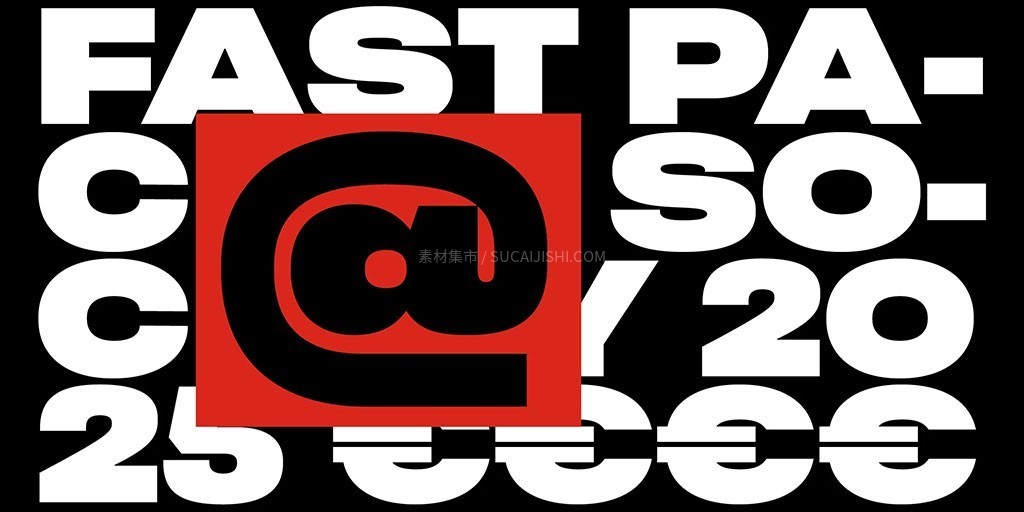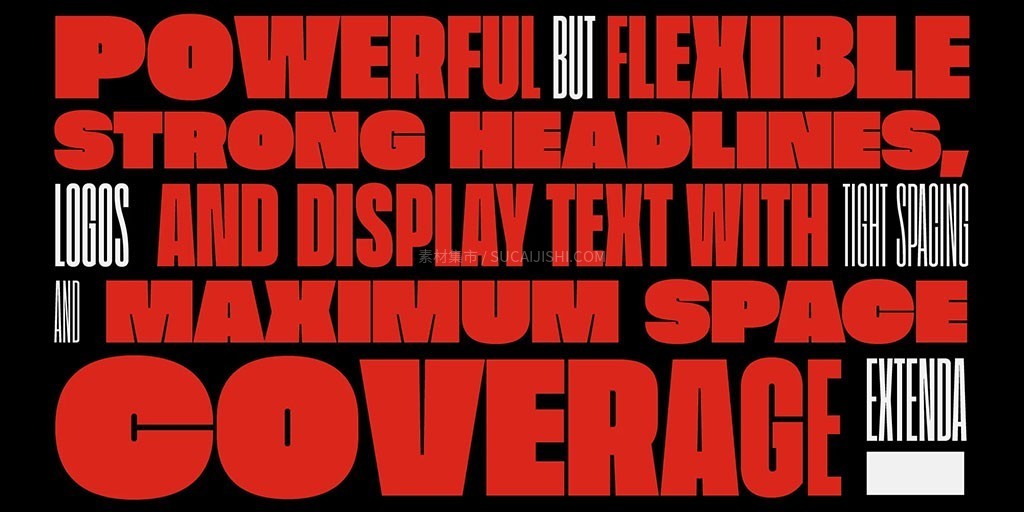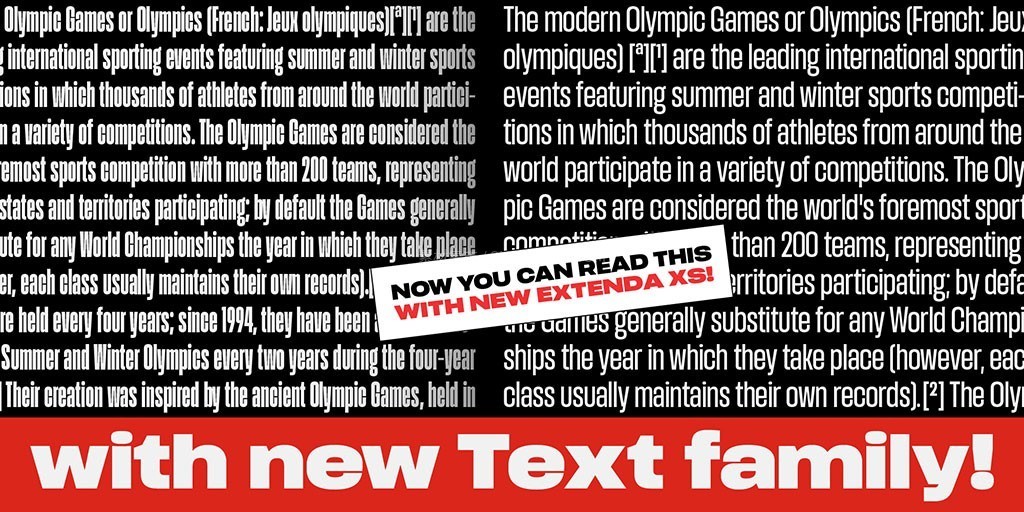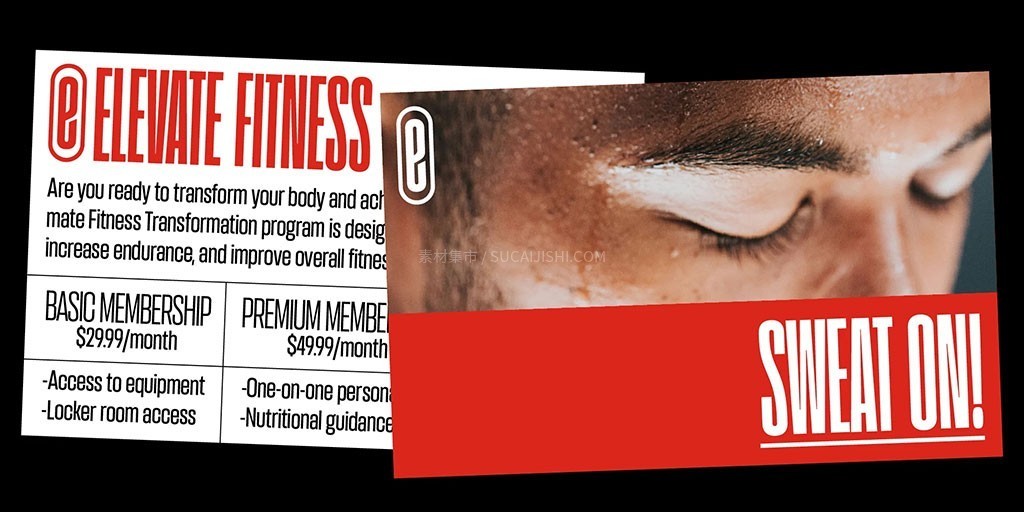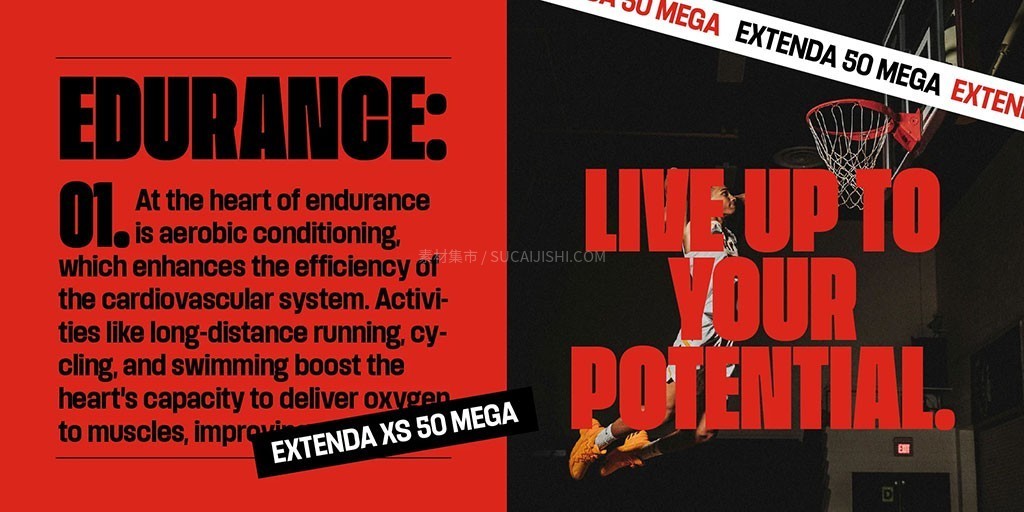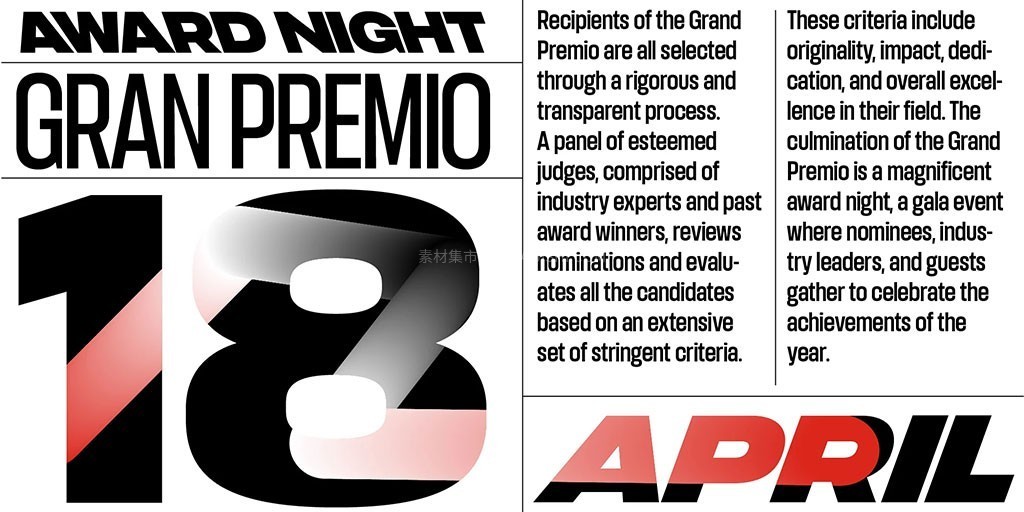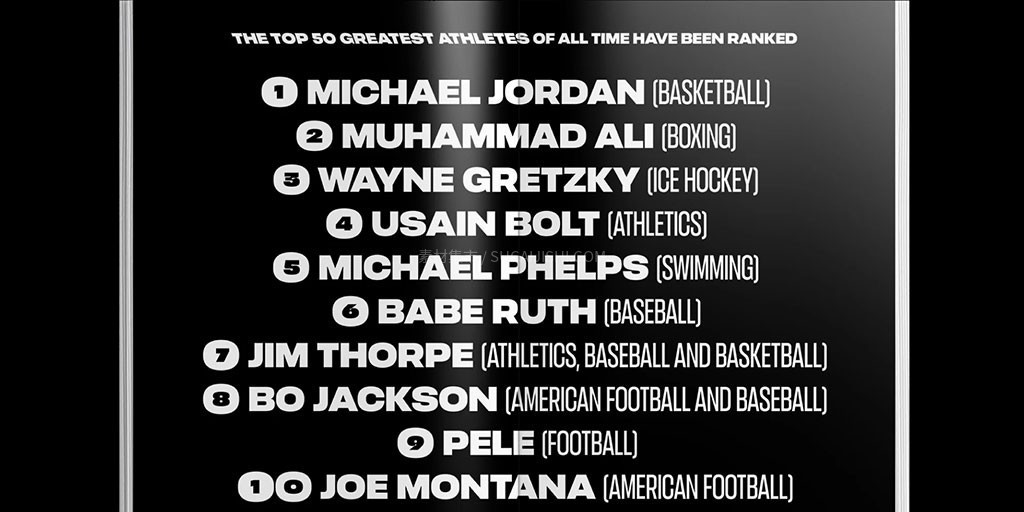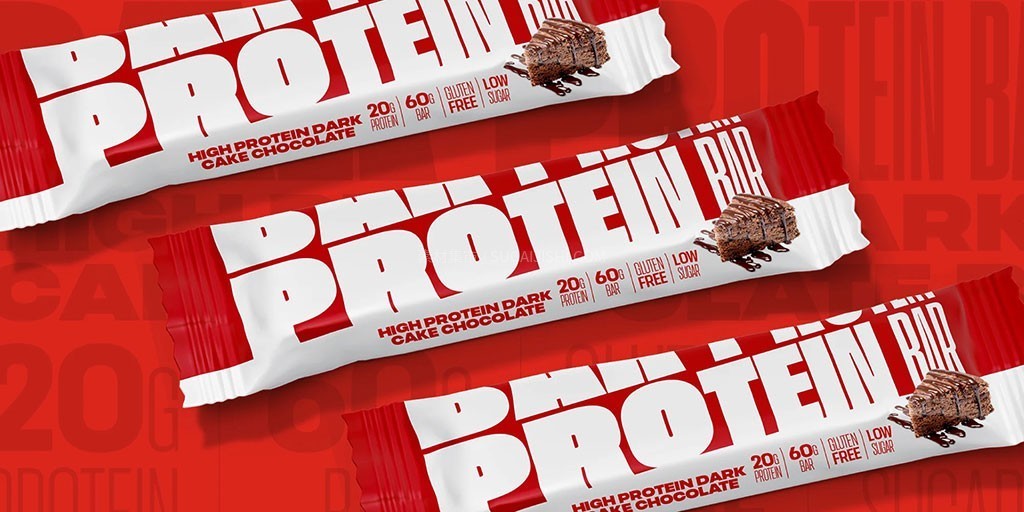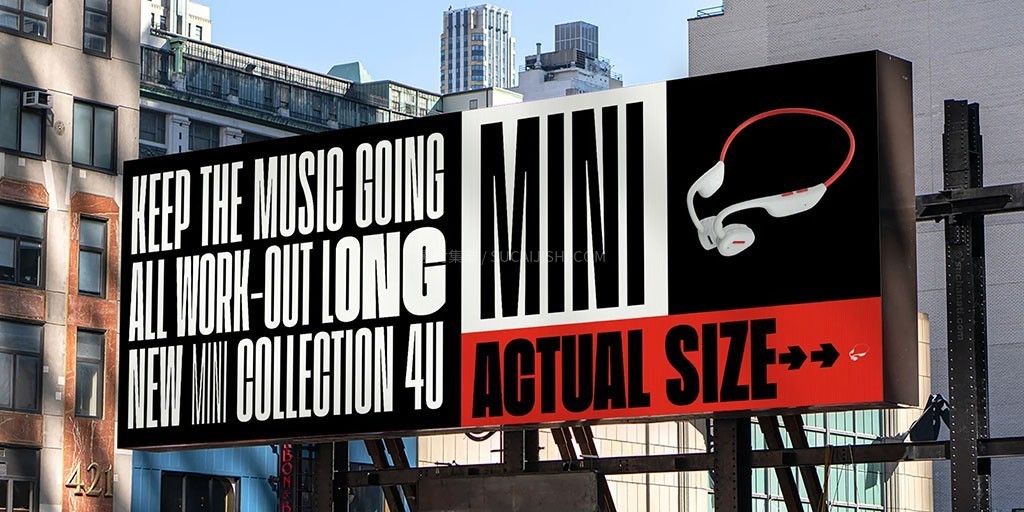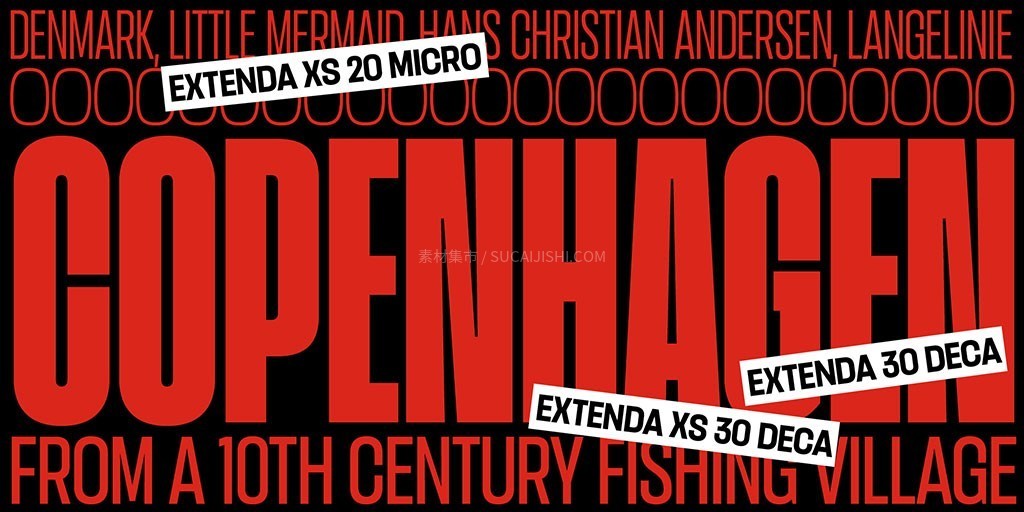
Extenda 超宽窄可变无衬线英文字体家族
这套由 Zetafonts 出品的专业无衬线西文字体家族,涵盖了从极致超窄到极限超宽的精细宽度体系,包含 67 款静态款式与 1 款可变字体(Variable Font),支持多国语言与丰富的 OpenType 高级排版特性,帮助你打造出兼具空间张力、紧凑视觉冲击力与现代高级感的标题与品牌视觉。